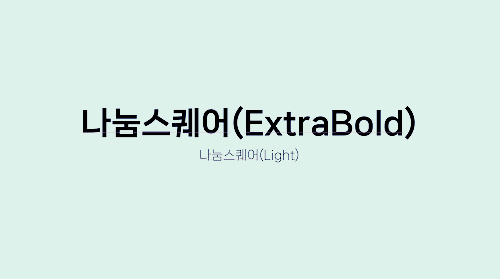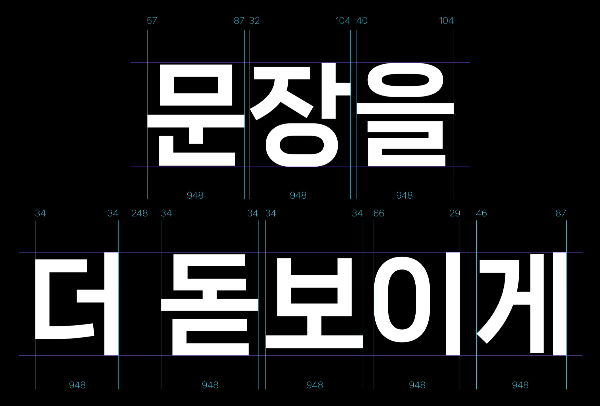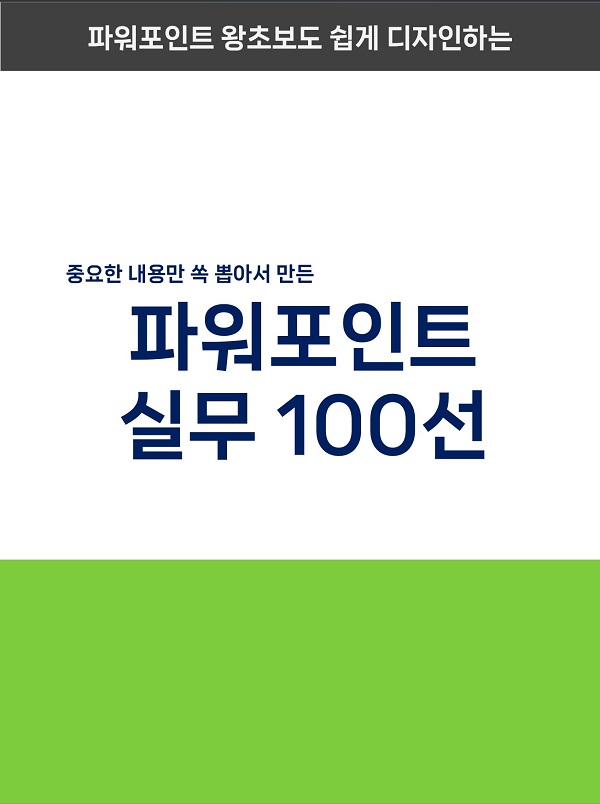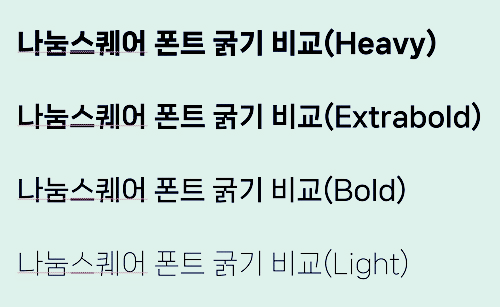
이번에 소개드릴 폰트는 나눔스퀘어NEO 폰트입니다.
나눔스퀘어 폰트는 총 4가지 굵기로 구성되어 있습니다.
- Heavy(가장 굵은)
- Extrabold(중간 굵은)
- Bold(굵은)
- Light(얇은)
폰트 특징
사진으로 보면 알 수 있듯이 문장을 굉장히 꽉 차보이게 하는 폰트입니다. 그래서 본문보다는 제목에 사용하기 좋은 폰트입니다. 꽉차보이는 구성의 폰트들은 본문에 사용할 경우 자칫 답답함을 느끼게 할 수 있습니다. 두께감이 있는 폰트들을 제목에 사용하고 세련미와 여유로움을 느낄 수 있는 폰트를 본문에 활용하는 이유이기도 합니다.
- 네이버 브랜드 폰트
- 직선적인 형태의 두께감이 살아있는 폰트
- 주목시키는 제목을 만들기에 우수한 폰트
그럼 폰트를 활용한 예제를 안 볼 수가 없겠죠?
일단 Letter 크기의 바탕에 간단하게 폰트와 색감들을 입혀보았습니다.
확실히 제목으로 깔끔함이 느껴집니다. 전자책이나 카드뉴스에 활용하기 좋은 폰트가 맞습니다.